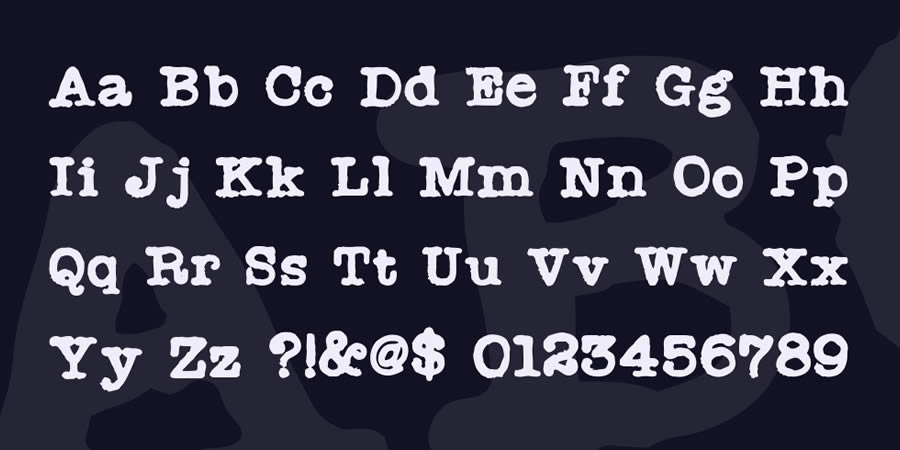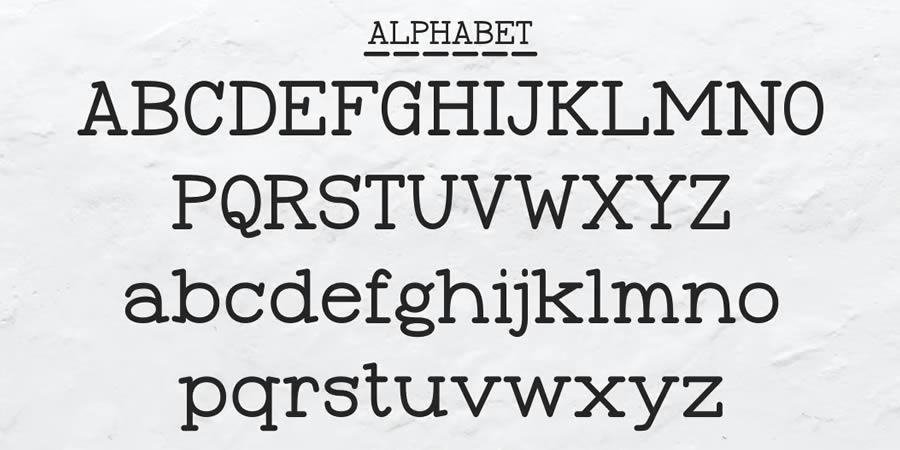
15+ freie fonts in typewriter style
Schreibmaschinenschriften können Ihren kreativen Projekten einen einzigartigen Stil verleihen. Ihre abgenutzten Buchstaben und subtilen Tintenflecke imitieren die charakteristischen Merkmale von Vintage-Schreibmaschinen. Sie eignen sich hervorragend für Projekte wie Poster, Branding oder Einladungen, die einen Vintage-Look benötigen.
Die meisten Schriften in dieser Sammlung wurden digital gestaltet und von klassischen Schreibmaschinen inspiriert. Wir haben aber auch einige Schriften aufgenommen, die von getipptem Text echter Schreibmaschinen gescannt wurden und originale Eigenheiten wie verblasste Tinte und ungleichmäßige Anschläge aufweisen.
Egal, ob Sie nach einer sauberen, eleganten Schrift oder einem abgenutzteren, authentischen Look suchen – in dieser Sammlung teilen wir einige der besten kostenlosen Schreibmaschinenschriften, die Ihren Projekten eine klassische Note verleihen.
Die kostenlose Schrift „Tox“ imitiert den eingedrückten Tinten-aufs-Papier-Effekt, den man typischerweise bei alten Schreibmaschinen findet. Ihre rauen und ungleichmäßigen Ränder machen sie perfekt für Vintage- oder Industrie-Projekte.
Tox kostenlose Schreibmaschinenschrift
„Postmark Typewriter“ hat einen sauberen, aber leicht verwitterten Stil. Die dünnen Linien der normalen Strichstärke und gelegentliche Tintenflecke verleihen ihr ein nostalgisches Gefühl. Diese Schrift eignet sich für Projekte, die einen authentischen Schreibmaschinen-Look benötigen.
Postmark Vintage Schreibmaschinenschrift
„Royal Quiet Deluxe“ ist eine kostenlose Schrift, die mit echten getippten Buchstaben einer Royal Portable-Schreibmaschine aus den 1950er Jahren erstellt wurde. Wenn Sie eine Schreibmaschinenschrift mit einem klaren, einheitlichen Stil und authentischen Störungen und Fehlern suchen, ist dies die richtige Schrift für Sie.
Royal Quiet Deluxe kostenlose Schreibmaschinenschrift
Mit ihren kräftigen Strichen und abgenutzten Zeichen wirkt „Ron’s Typewriter“ schwer und dramatisch, was sie perfekt für Poster-Designs macht. Diese Serifenschrift gibt es in normaler, leichter und fetter Strichstärke.
Rons Serif Schreibmaschinenschrift
„Courier Prime“ modernisiert die klassische Courier-Schrift, behält aber ihr monospaced Design bei. Sie ist sauber, gut lesbar und vielseitig. Diese Schrift eignet sich gut für Code oder andere textlastige Dokumente.
Courier Prime kostenlose Schreibmaschinenschrift
Diese Schrift kombiniert die klassische Struktur einer Schreibmaschine mit einem handschriftlichen Gefühl. Das tintenverschmierte Erscheinungsbild und der ungleichmäßige Zeichenabstand verleihen ihr eine organische und persönliche Note. Sie umfasst normale, umrissene und kursive Strichstärken.
Inked Schreibmaschinenschrift
„Bygonest Typewriter“ ist eine abgenutzte und verwitterte kostenlose Schrift mit ungleichmäßigen Strichen und blassen Abdrücken. Ihre rauen Ränder lassen sie alt und gebraucht aussehen und erzeugen das Gefühl von alten Dokumenten oder getippten Briefen.
Bygonest kostenlose Schreibmaschinenschrift
„Typedeermono“ ist eine Schreibmaschinenschrift mit einem leicht verzerrten, handgedrückten Aussehen, das so gestaltet wurde, als wären die Buchstaben mit einem Gummistempel erstellt worden. Sie umfasst sowohl normale als auch Stempel-Varianten.
TypedeerMono Typewriter Stamp Schreibmaschinenschrift
„Radio Newsman“ ist eine kräftige Schreibmaschinenschrift, die von Nachrichtenredaktionen aus der Mitte des 20. Jahrhunderts inspiriert wurde. Ihre fetten Zeichen machen sie perfekt für Überschriften oder Vintage-Designs.
Radio Newsman Bold kostenlose Schreibmaschinenschrift
„Frontype“ ist eine saubere Serifenschrift mit leichten Unregelmäßigkeiten, die von traditionellem Schreibmaschinentext inspiriert wurde. Die subtilen Flecken erwecken den Eindruck eines frisch eingefärbten Schreibmaschinenbands. Sie ist perfekt für Retro-Projekte, die gut lesbar sein müssen.
Frontype kostenlose Schreibmaschinenschrift
„TT2020“ bietet eine moderne Variante klassischer Schreibmaschinenschriften. Seine präzisen Linien wirken zeitgemäß, behalten aber die Unregelmäßigkeiten bei, die Schreibmaschinenschriften ihren Charakter verleihen. Diese kostenlose Schrift gibt es in sechs verschiedenen Stilen.
TT2020 kostenlose Schreibmaschinenschrift
„Xerography“ ist eine kostenlose Serifenschrift, die das Aussehen einer abgenutzten Schreibmaschine oder Kopiermaschine nachahmt. Sie hat leicht raue Ränder mit verblassten Zeichen und einen soliden Stempelhintergrund. Diese Schreibmaschinenschrift wäre perfekt für auffällige Poster-Designs.